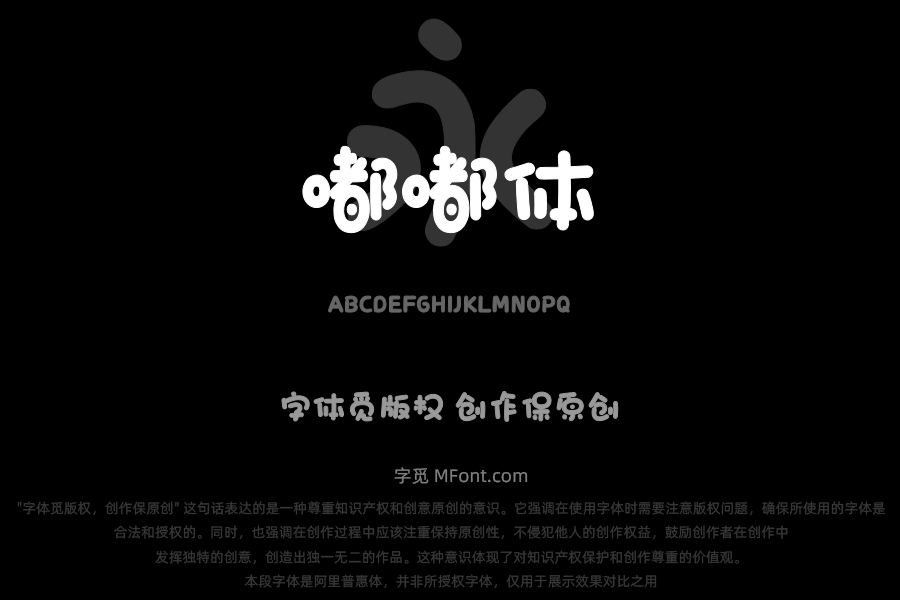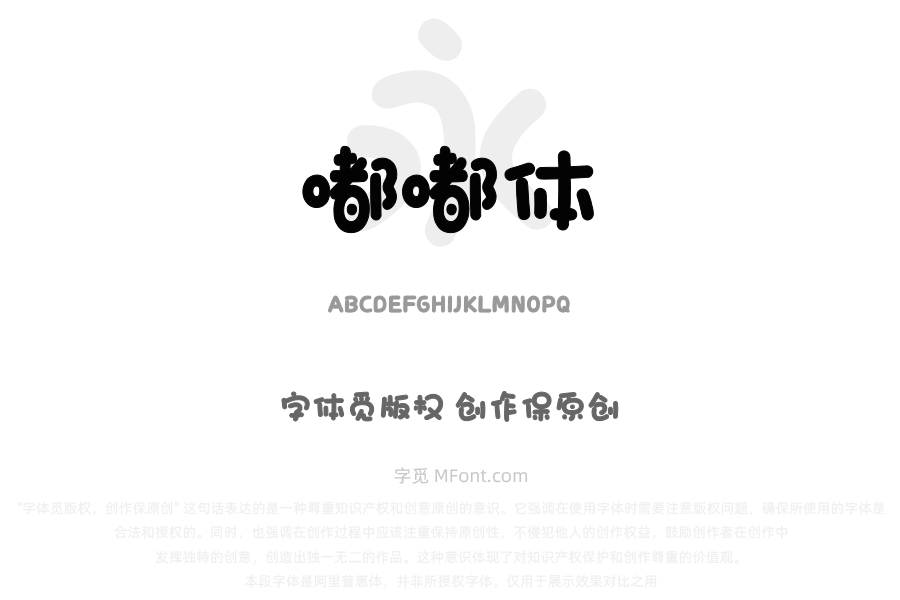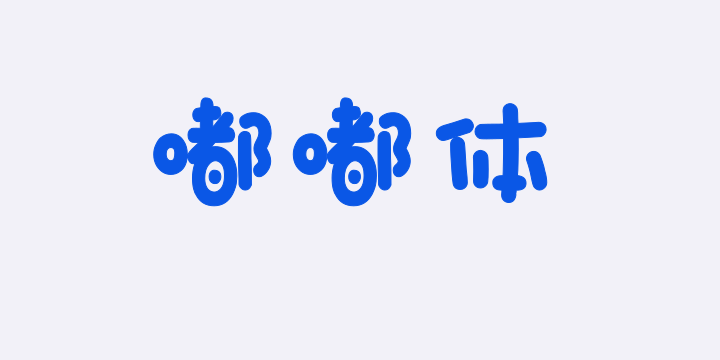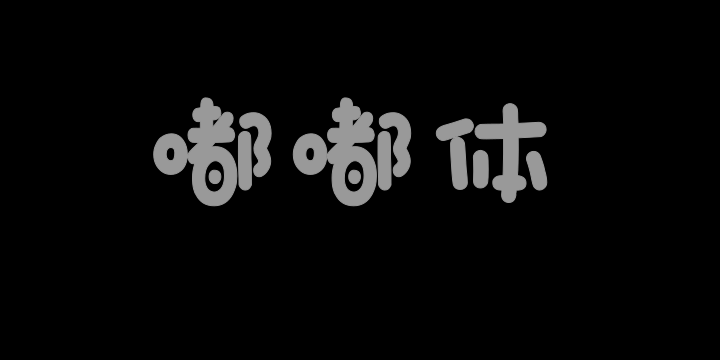
字体全名: 上首嘟嘟体
字体简介: 上首嘟嘟体,简体中文约6763字。这套字体笔画的圆润形态,如同给文字裹上一层柔软的 “情绪糖衣”,让其在视觉传达中自带亲和力;结构的灵动变形,恰似为文字赋予 “孩童般的好奇心”。 以独特的 “古趣新颜”,搭建起传统与现代、庄重与活泼的沟通桥梁,用可爱的视觉语言,重新诠释汉字的温度与魅力 。
所属分类: 卡通手写体